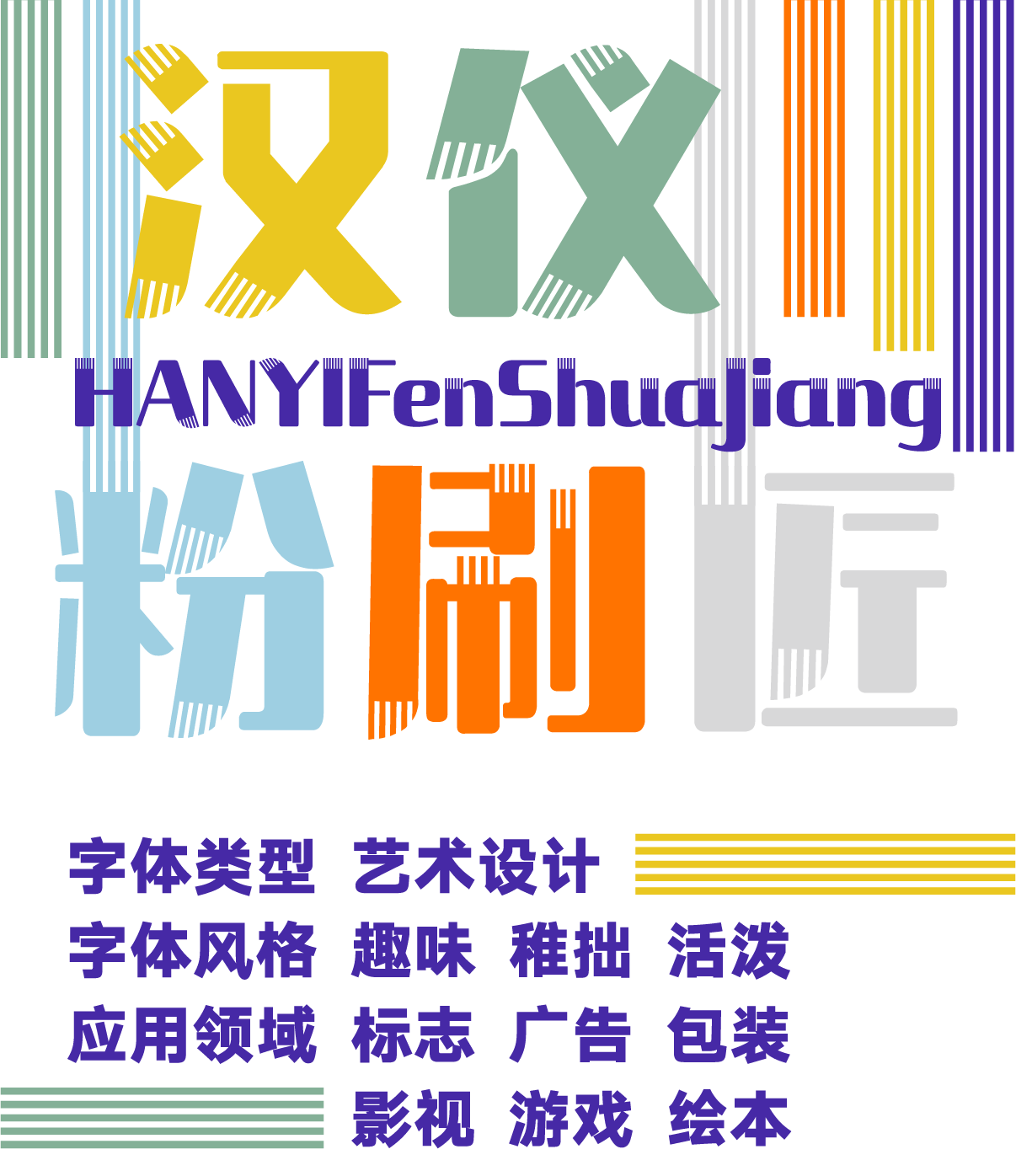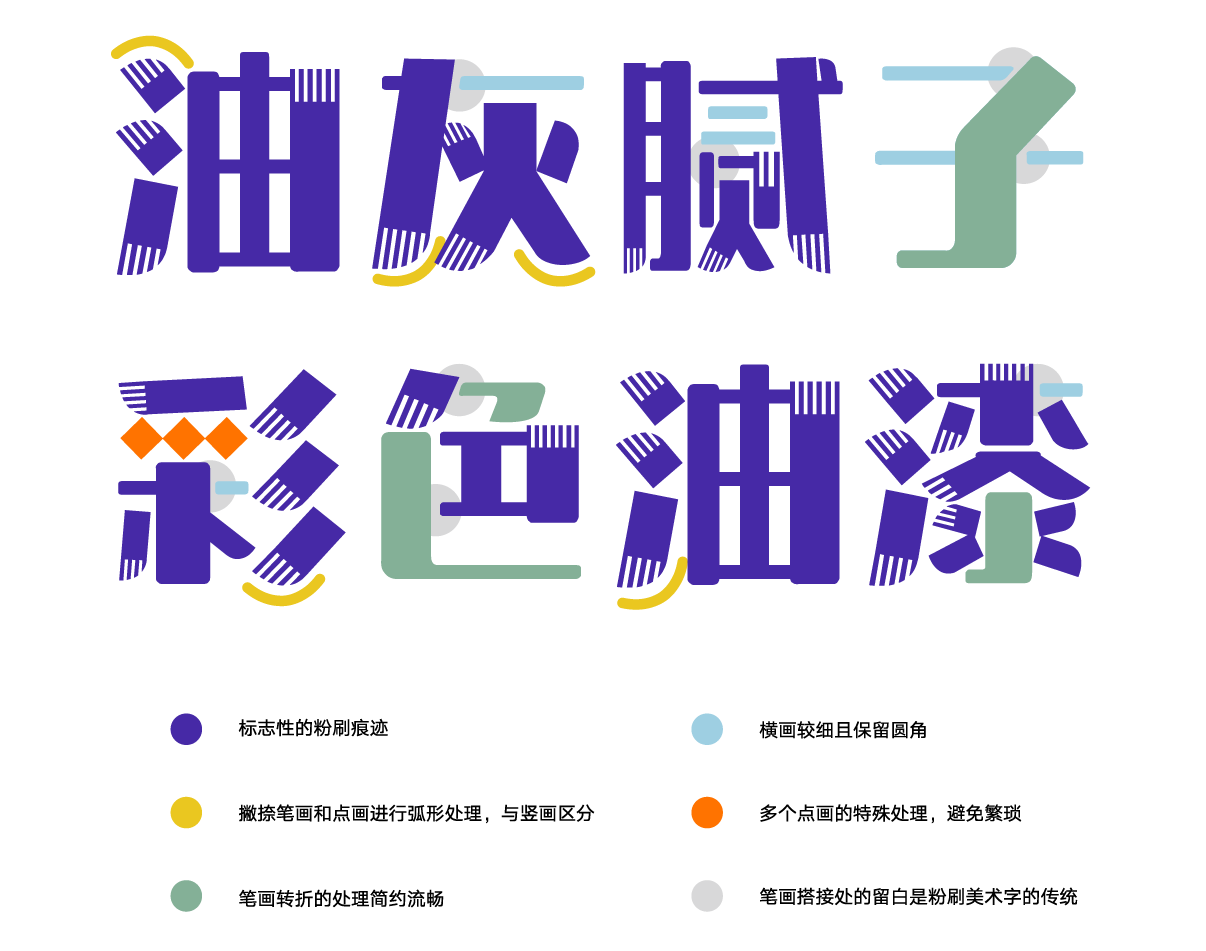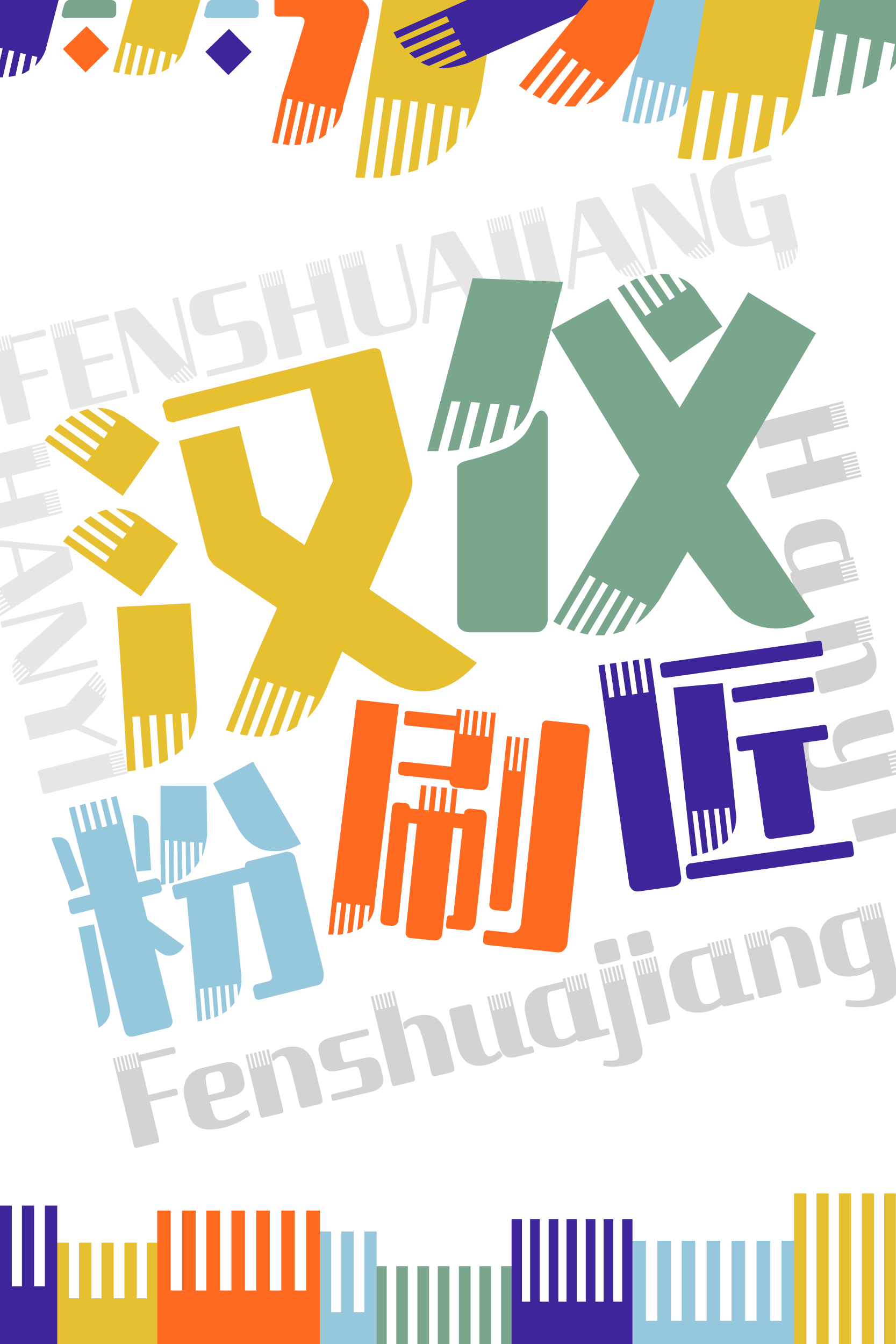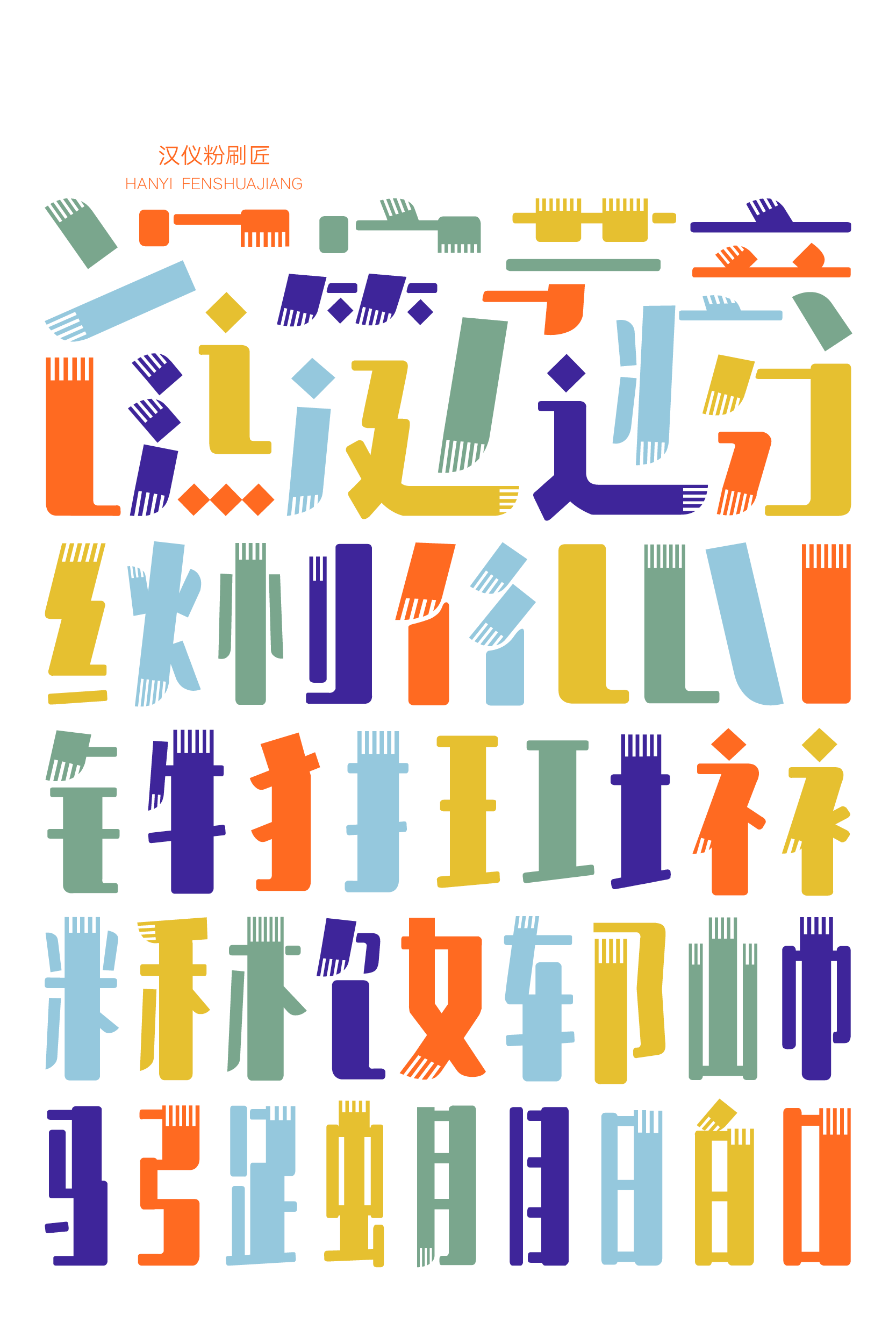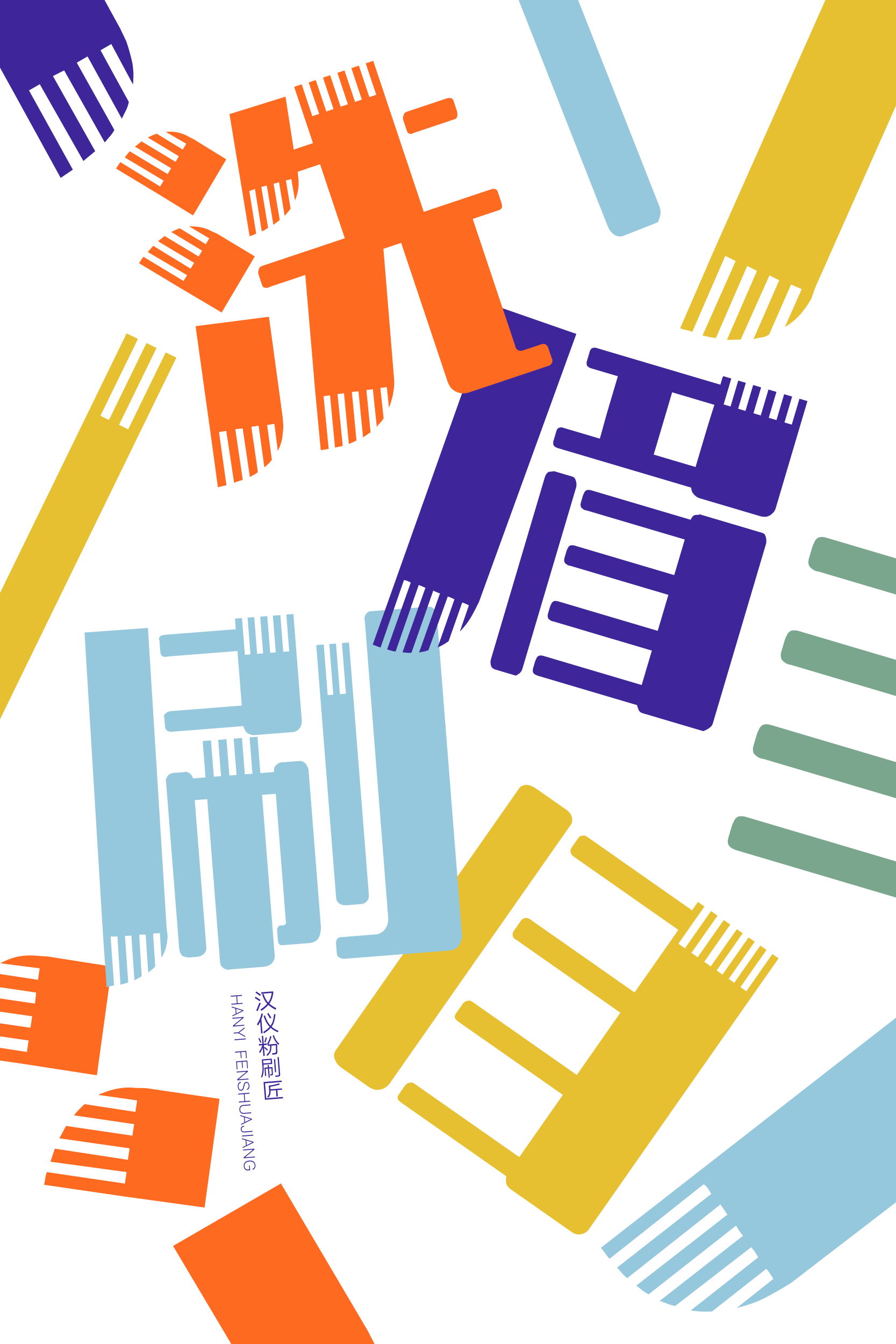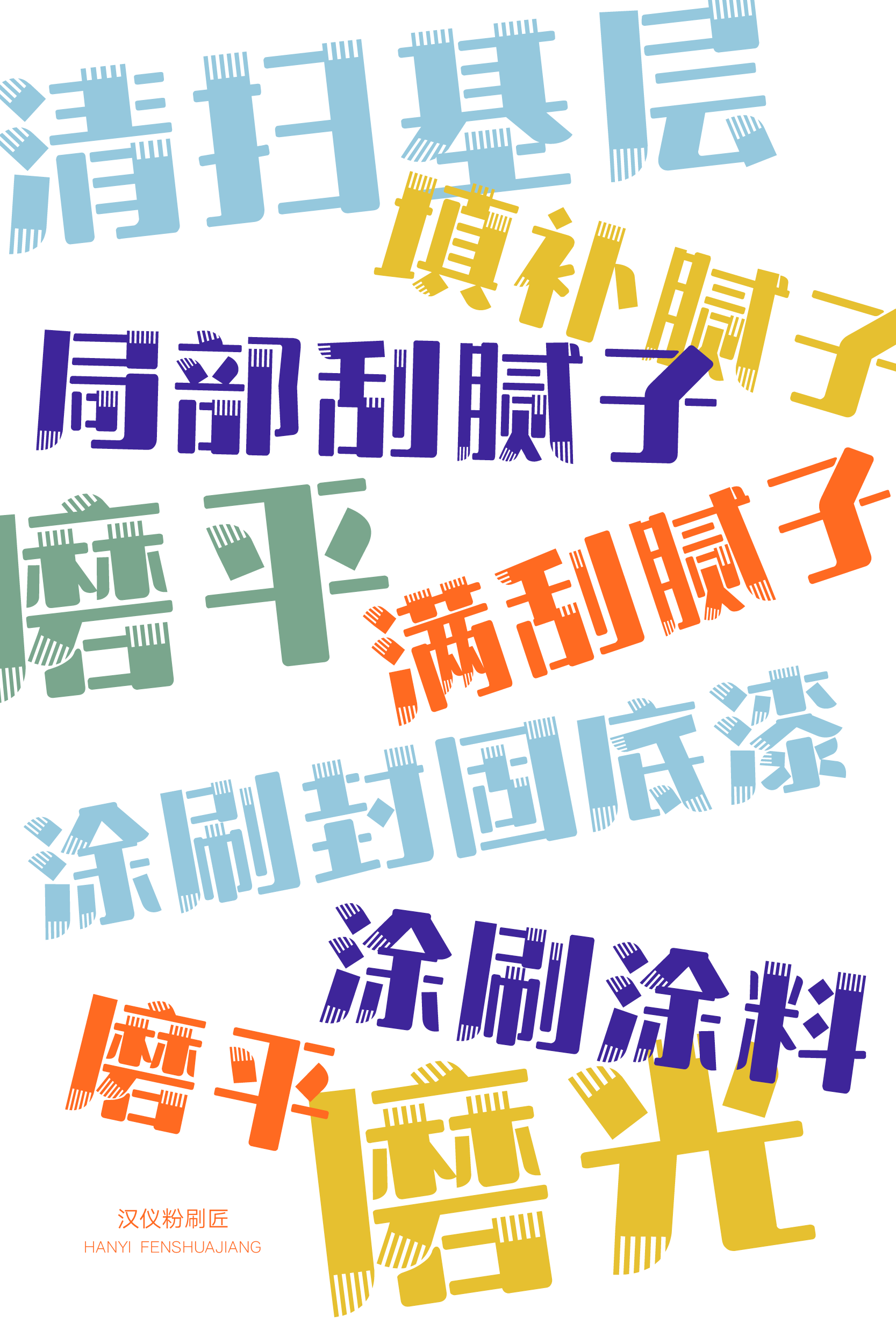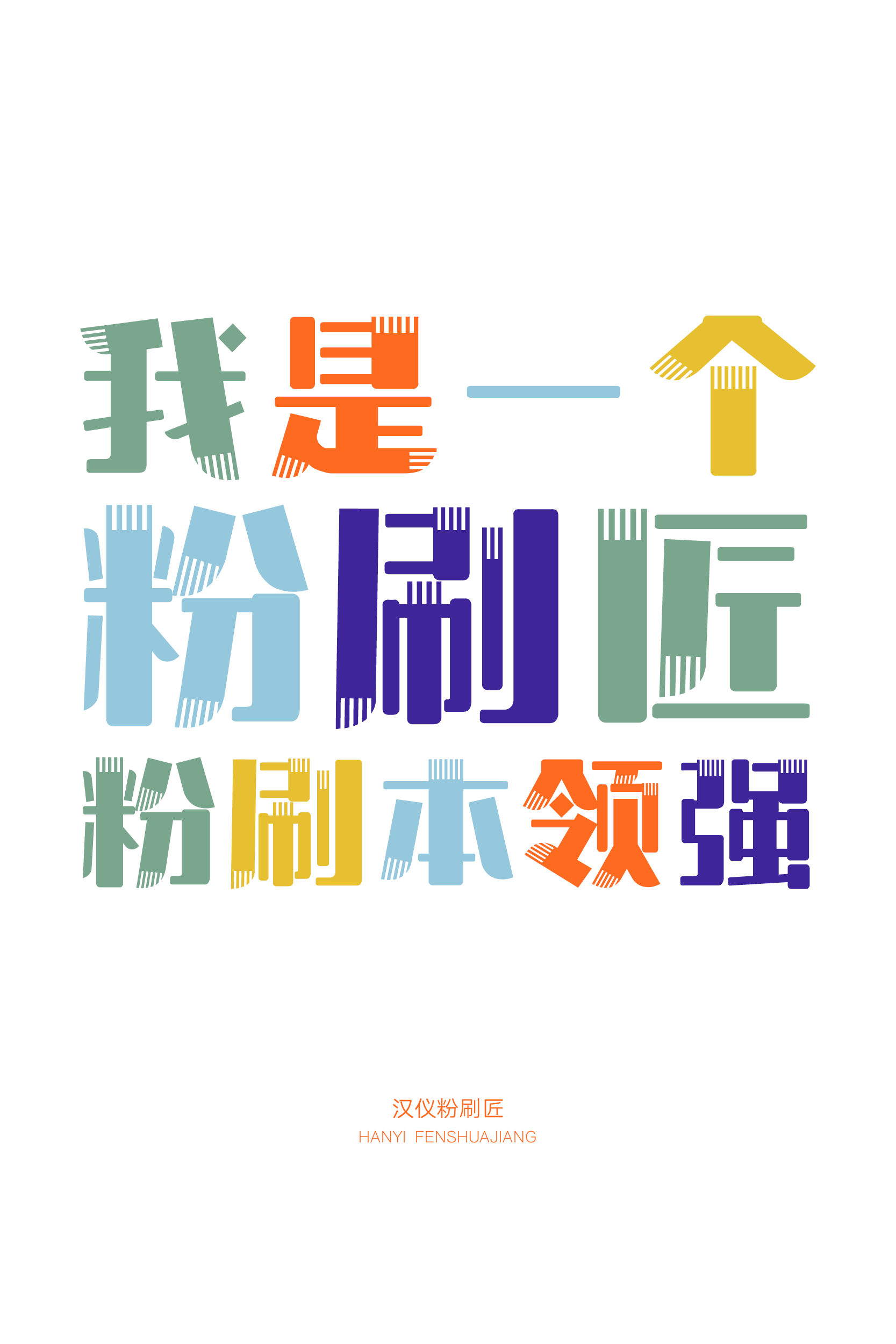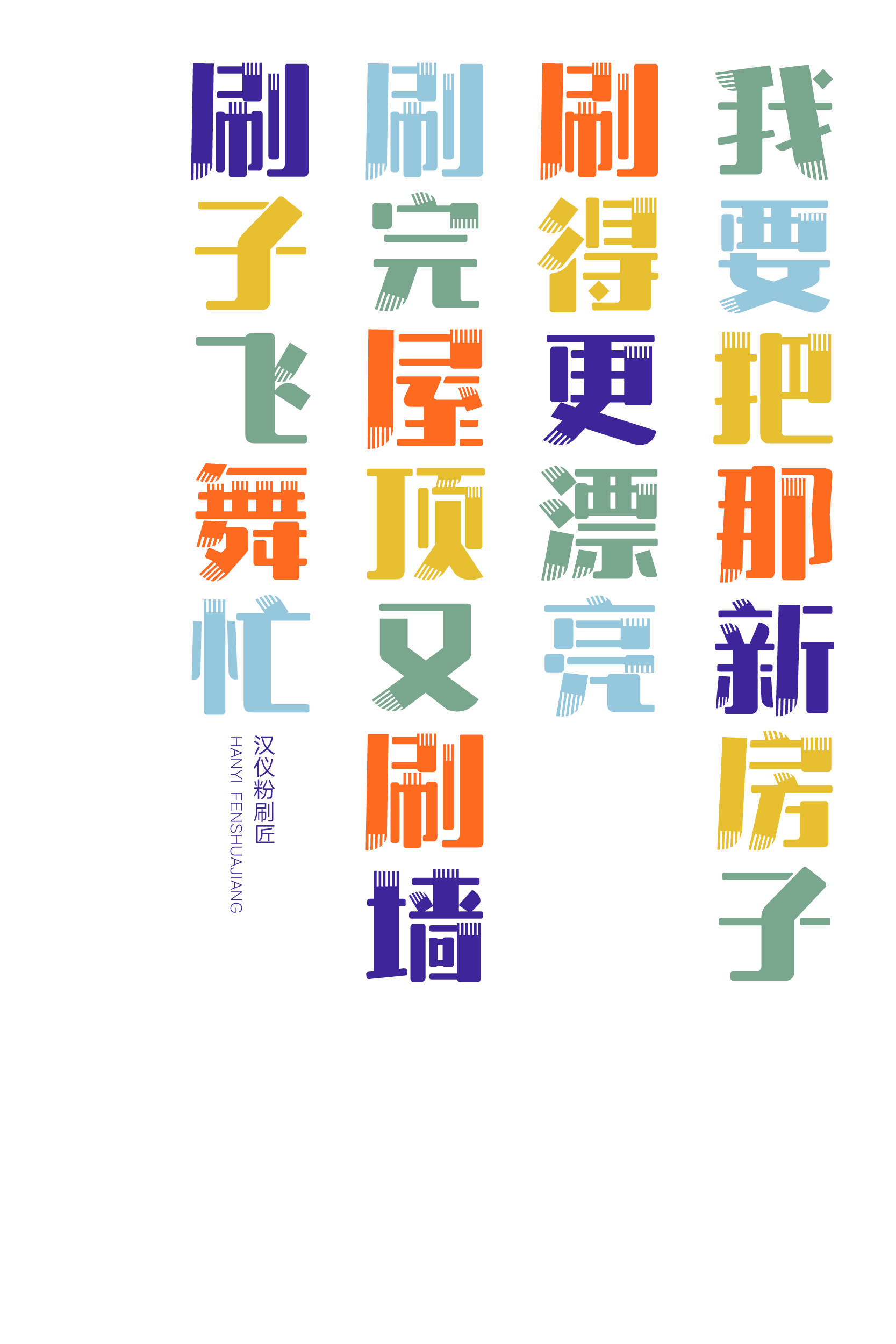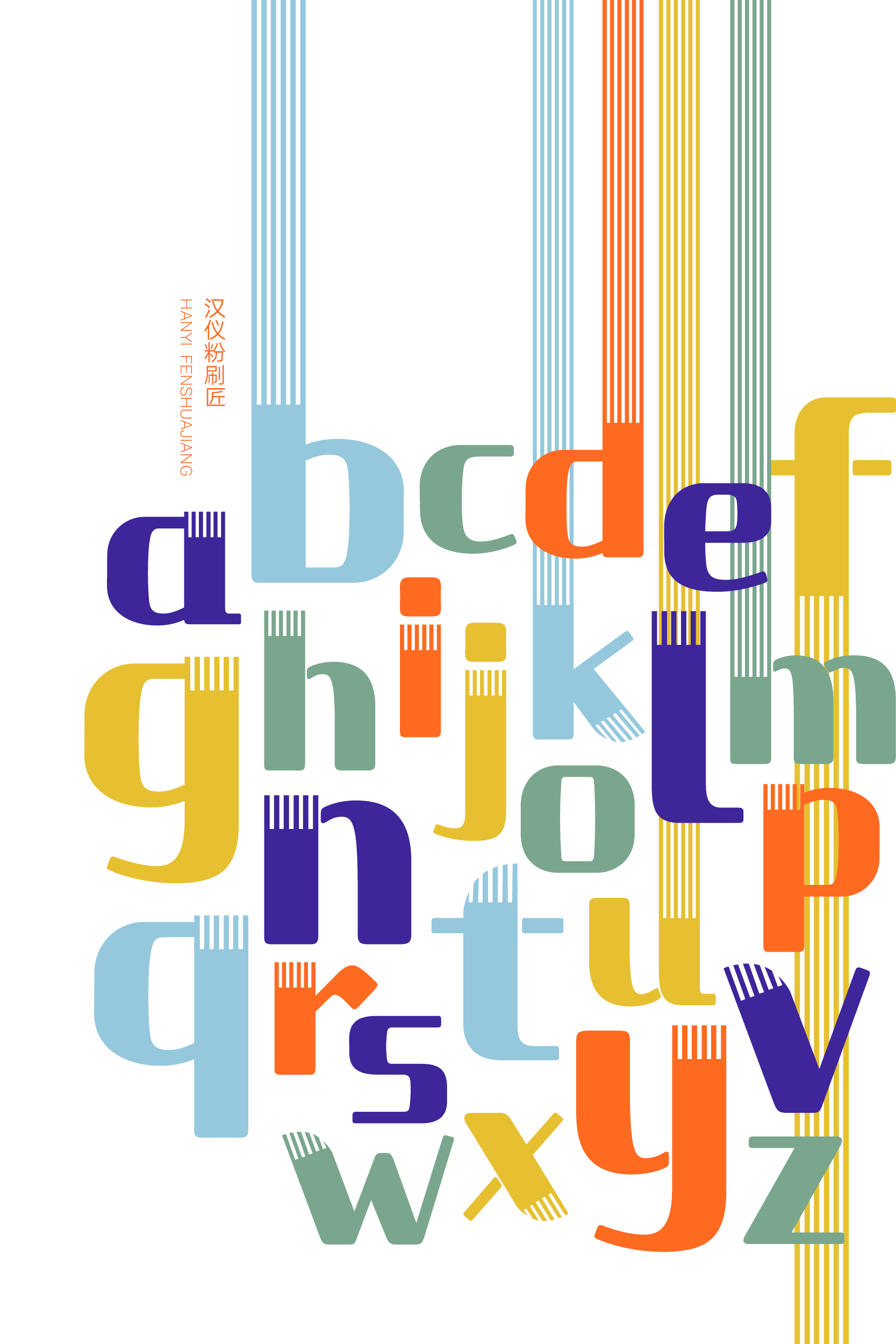
一款能让人自动哼歌的有趣字体
汉仪粉刷匠,粉刷本领强。整齐的字形、简约的笔画和粉刷留下的痕迹,组成了这款稚拙活泼的创意字体。汉仪粉刷匠适合作为标题字体应用于儿童绘本、少儿读物、玩具包装等多种使用场景,就像粉刷匠把新房子粉刷得更漂亮,这款字体也能把版面中的文本粉刷得更有趣。
字形方方整整,规规矩矩。
粉刷留下的痕迹是这款字体标志性的特征。
笔画造型简约,细节处理丰富有巧思。
汉仪粉刷匠的西文部分由汉仪字库西文字体设计师李田宇创作,同样粉刷出整齐稳定的字形和简约流畅的笔画,中西文搭配使用凸显汉仪粉刷匠活泼稚拙的风格。